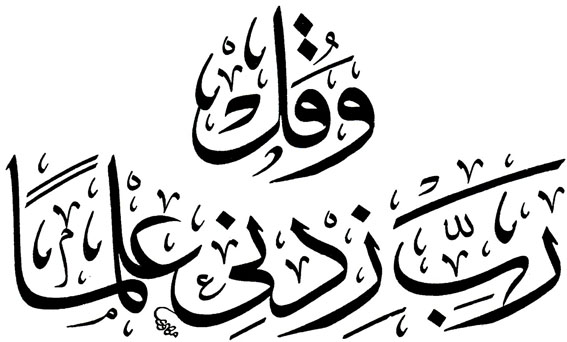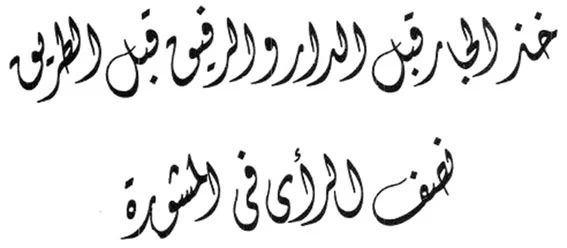
لأنه عرف رسمياً لدى الأتراك بعد فتح السلطان محمد الفاتح العثماني القسطنطينية في عام 857هـ ،
وأول من وضع قواعده منهم إبراهيم منيف الذي عاش في عهد السلطان محمد الثاني
ووضع قواعده في البلاد العربية الخطاط مصطفى غزلان ، ولذلك سمي بالخط الغزلاني نسبة للخطاط مصطفى غزلان
الذي أدخل عليه الشكل الجمالي الذي يتلائم مع جمال الخطوط العربيه وقام بوضع قواعده وأسسه وطرق كتابته بشكل جمالي.
وسمي كذلك بخط رقعة الباب العالي لأنه كان يستخدم في المراسلات الرسميه لسلطان الآستانه ( الباب العالي ).
وسمي الخط الديواني كذلك بخط الرقعه لأنه تم استنساخ حروفه وقواعده من حروف وقواعد الخط الرقعه.
الخط الديواني العادي التقليدي
الخط الديواني التقليدي المطور
الخط الديواني التقليدي المزخرف
خط الديواني المجد الملكي الفارسي
الخط الديواني الجلي
الخط الديواني الجلي المزخرف
الخط الديواني الذهبي الغزلاني
الخط الديواني الفارسي
الخط الديواني الفارسي الحديث المطور
الخط الديواني الفارسي خيال
الخط الديواني الملكي
الخط الديواني جلي الصمت
الخط الديواني الهاوي
الخط الديواني الفارسي الغريب